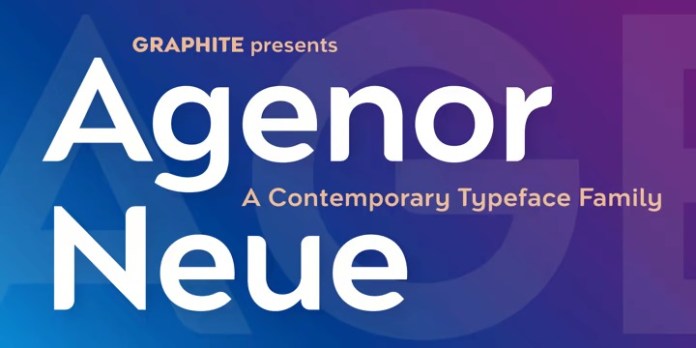
Agenor Neue 字体家族
Agenor Neue Sans Serif 字体
这是一种用扩展比例修改的新怪诞字体。这种字体具有现代外观,适合显示和正文。圆形边缘的选择性使用赋予它独特而鲜明的特征。Agenor Neue 系列有 7 种权重,非常适合用于标识、标题、标题和任何其他显示用途。
设计师 :石墨